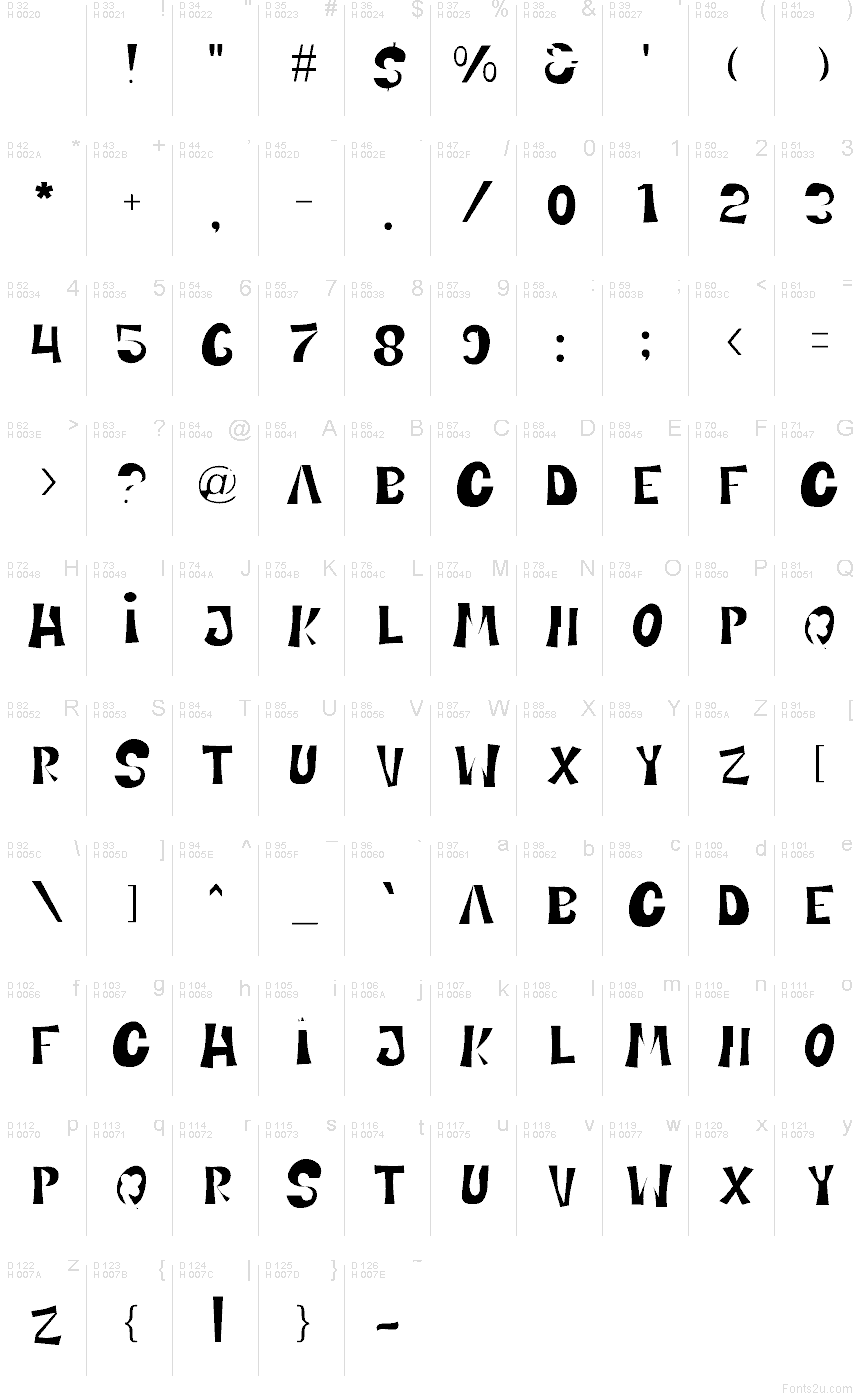
King Jack Style Inner de Cikareotype Studio est une police de type cartoon gratuite au caractère dynamique, évoquant le papier découpé. Ses majuscules sont audacieuses et malicieuses, avec des silhouettes épaisses, des encoches marquées et des bords irréguliers qui donnent aux lettres un aspect sculpté et volontairement décalé.
Elle est idéale pour les affiches, l'image de marque pour enfants, les packagings ludiques, les titres façon comics et les textes courts où une police pleine de peps peut insuffler toute l'ambiance. Utilisez-la pour vos logos, lettrines ou monogrammes si vous souhaitez que vos lettres expriment un style artisanal et affirmé plutôt qu'un rendu neutre.